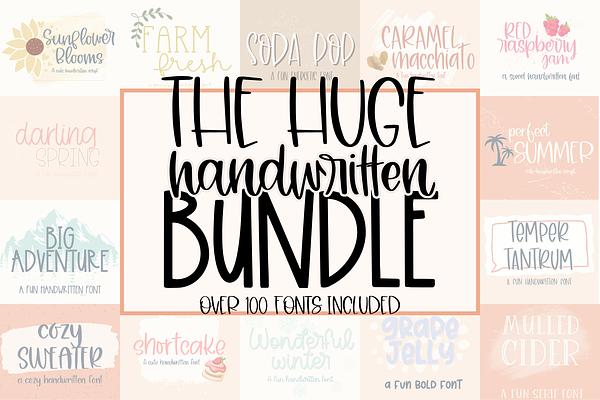
100款手写体字体合集
Huge Handwritten Font Bundle
这是一套包含超过100款手写风格字体的合集,画面展示了多种手写字体,包括自然手写、活泼手绘、优雅书法等风格,配色以柔和的米色、粉色、浅蓝为主,适合用于品牌标志、海报设计、包装设计、标题排版等场景,整体风格温馨、亲切、富有个性。
100款手写体字体合集